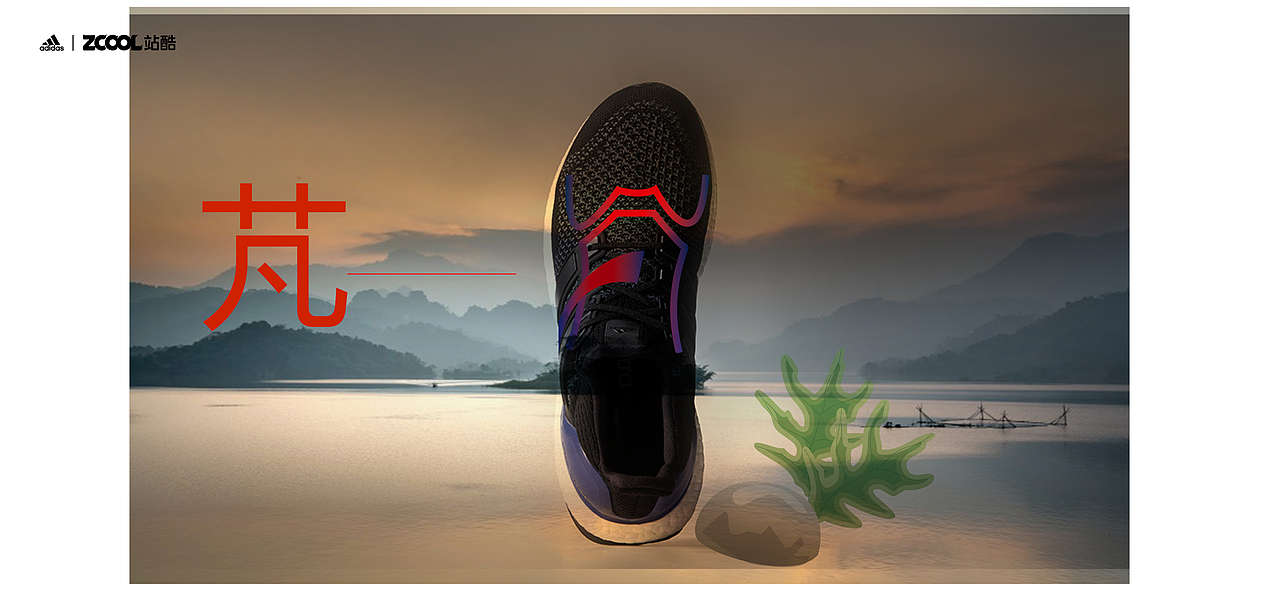
菲凡
菲凡(芃)
菲同寻常! 菲同凡响!
阿迪达斯ADIDAS一直深受运动者的喜爱;招牌BOOST鞋底,
以菲凡的身份挤身于同行的前列!
“菲”:“艹”-"W"图;“非”-鞋身侧面三条横杠条;左/右系绳口两竖篮条;组成一个菲字。
“芃”与“凡”是同音字。也与菲字对称“艹”;
芃:"艹"- "W";"凡"-系绳鞋口形成几;"、"成一撇,运动的速度象征;
篮红渐变色增加鞋形的线条感,弦酷的色彩,化身为运动者的冲劲和拼博热情!!!
阿迪达斯运动鞋,以优质产品,给运动者带来菲凡的体验!!!